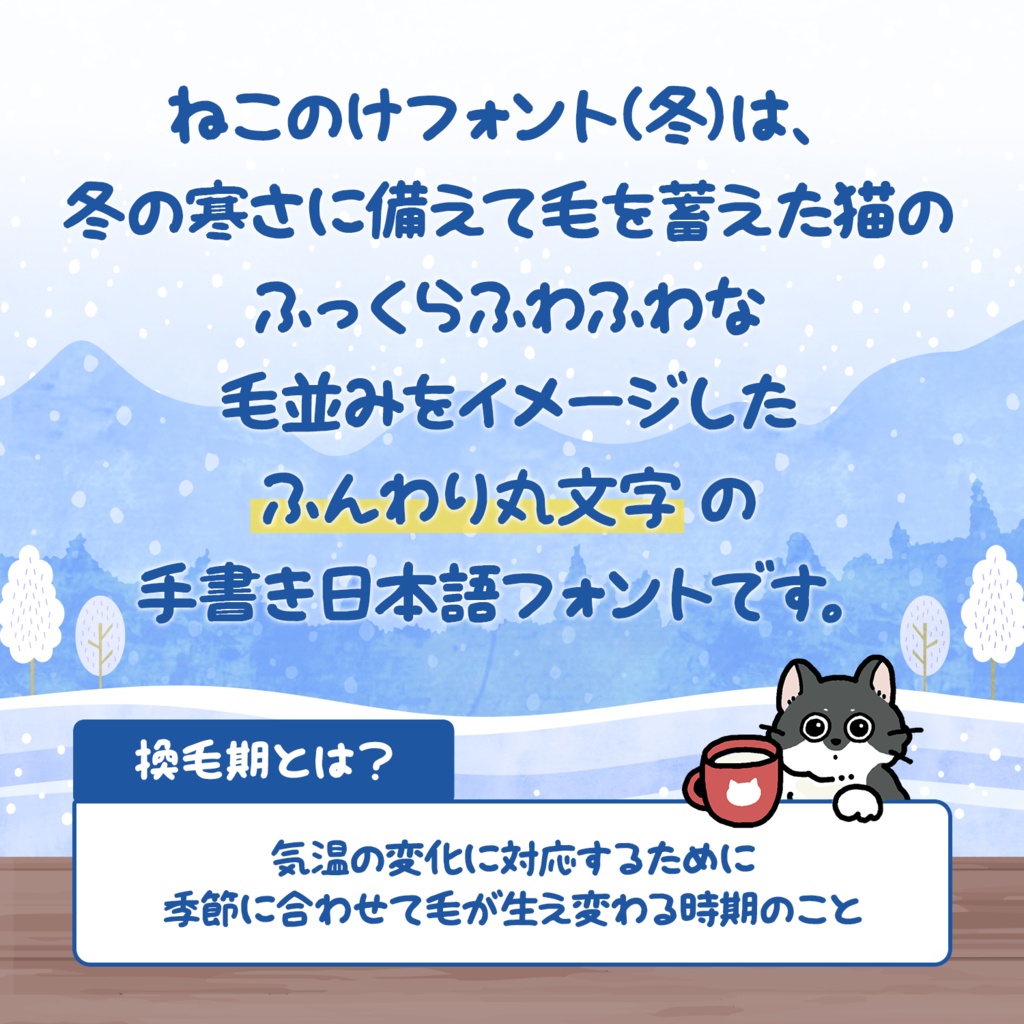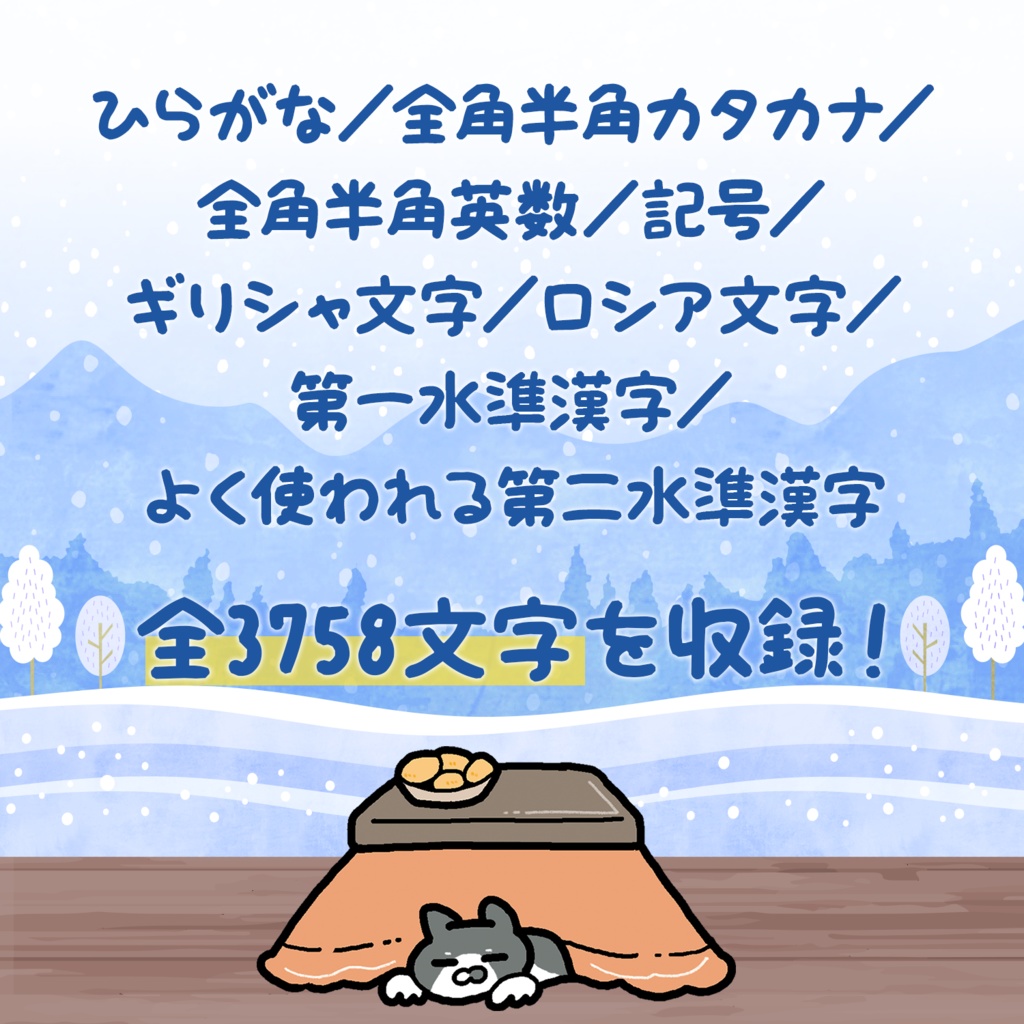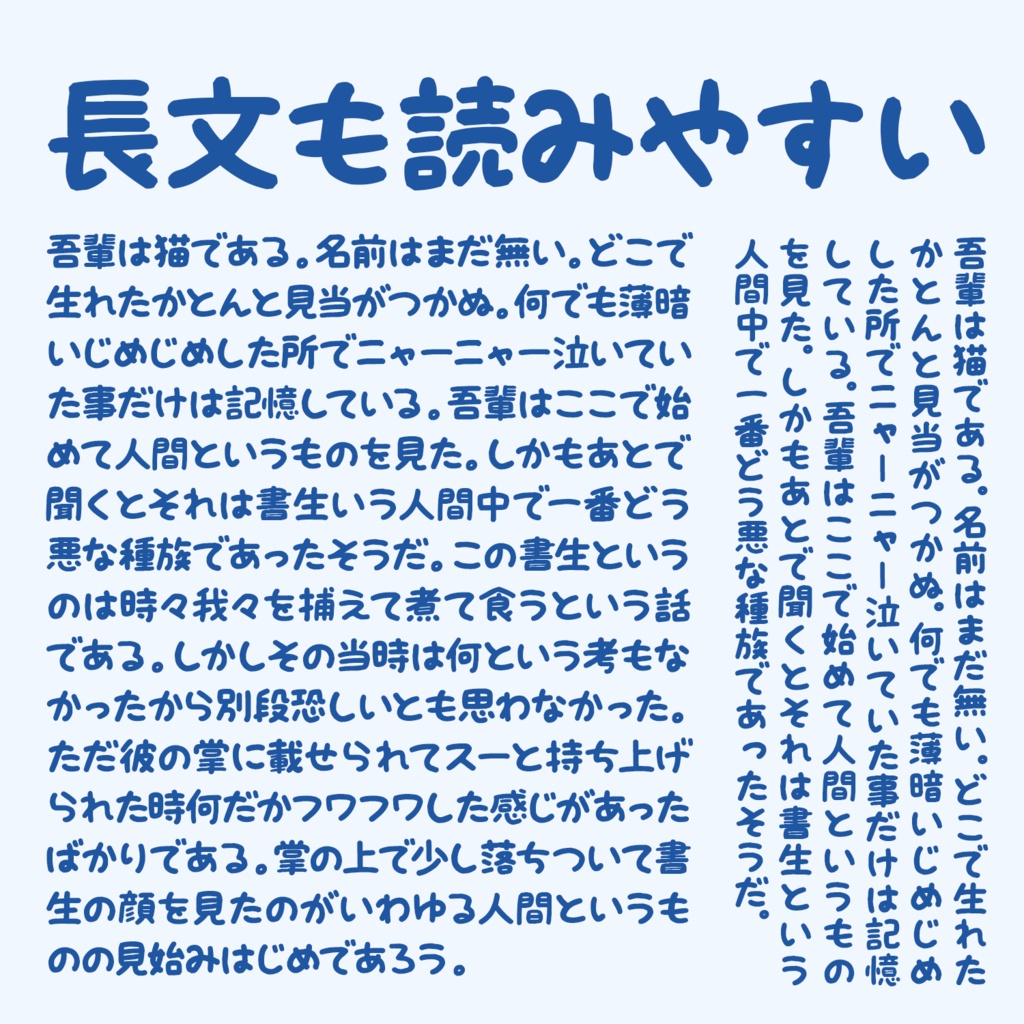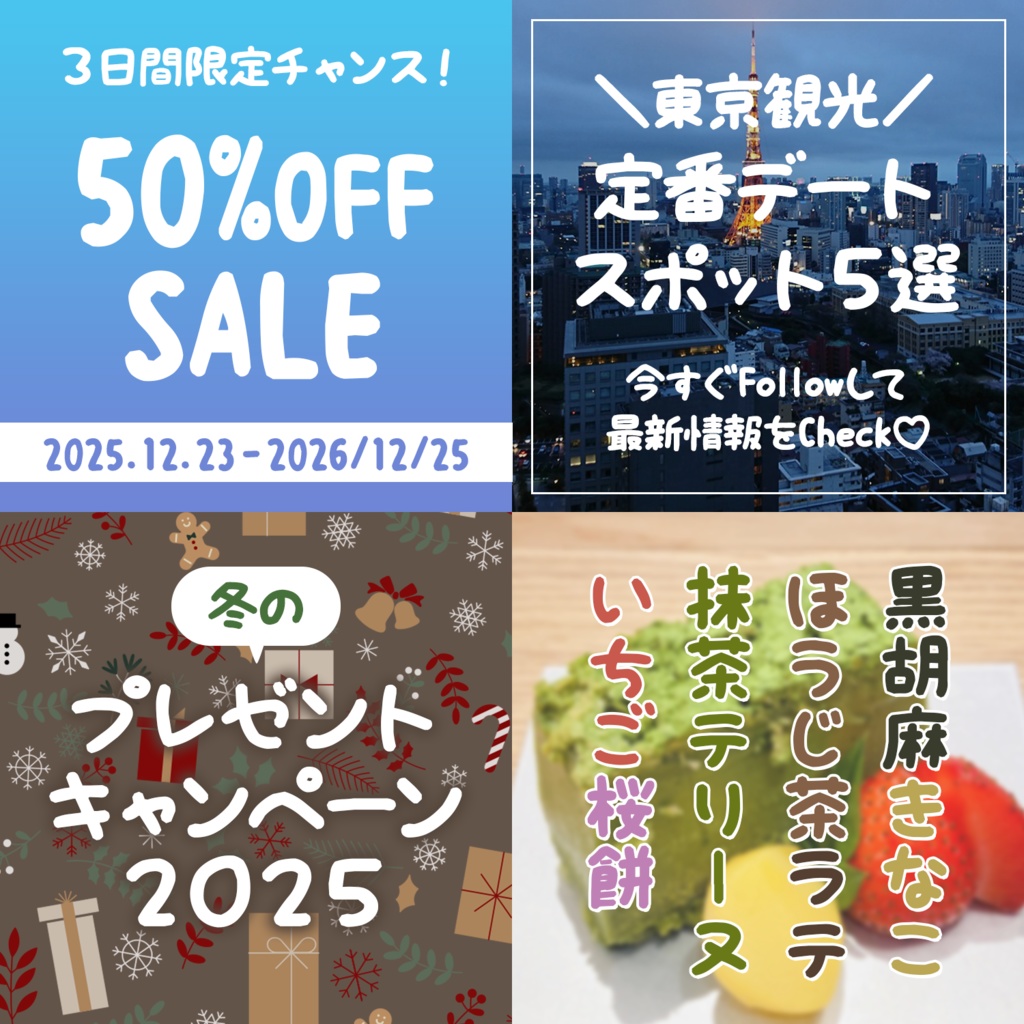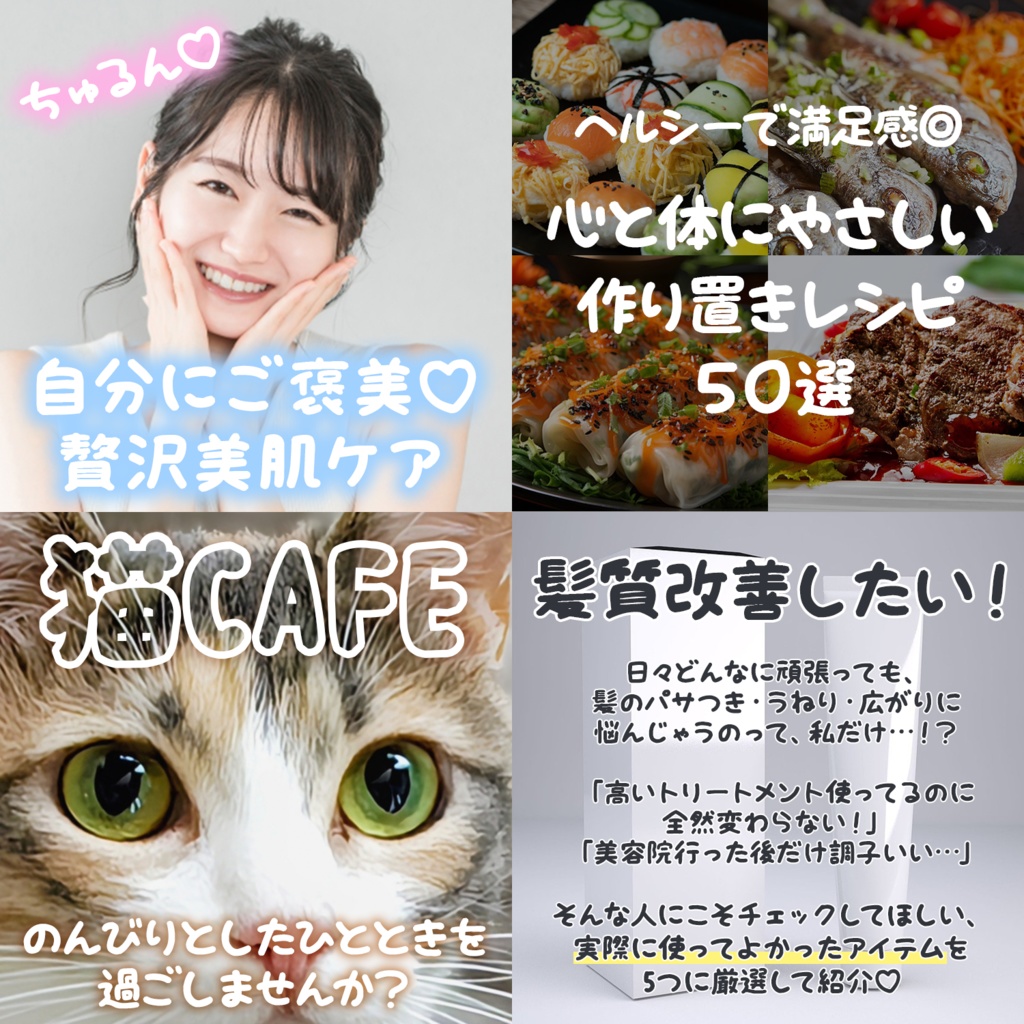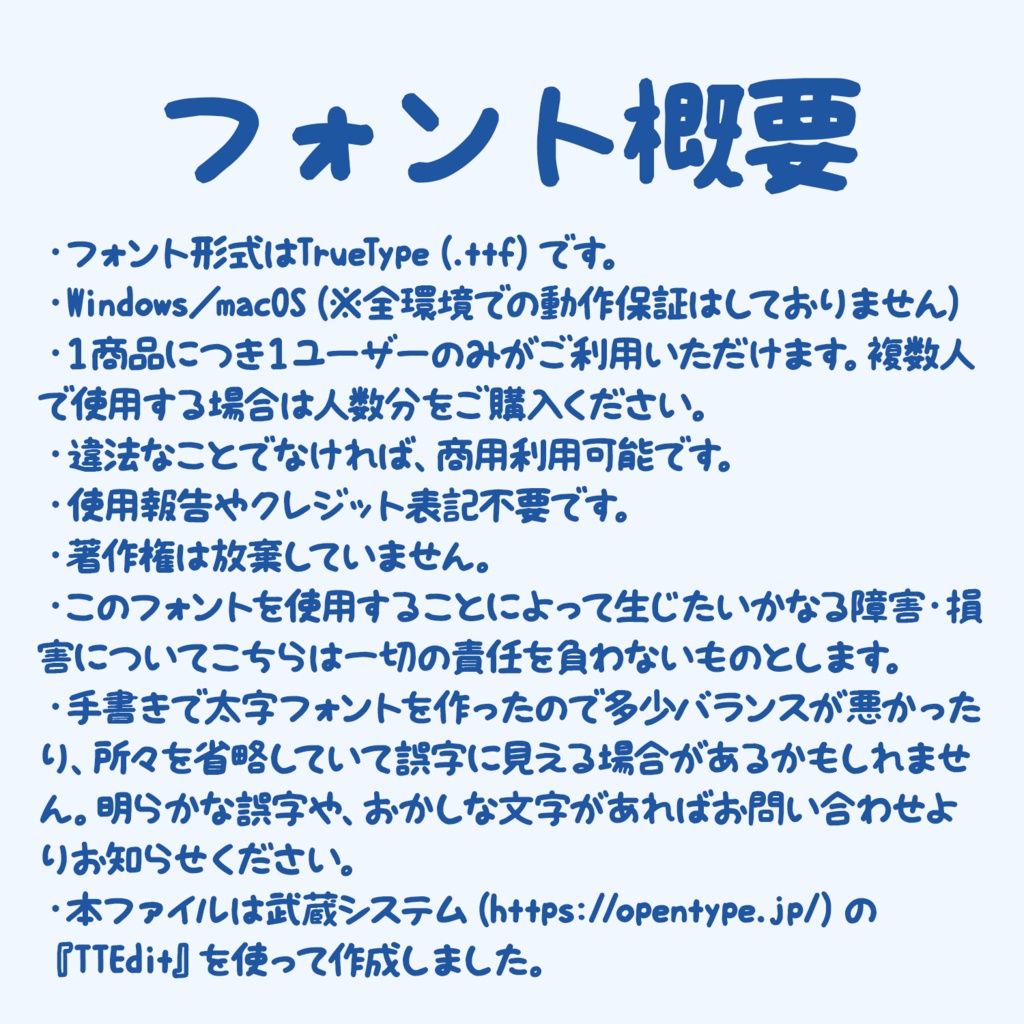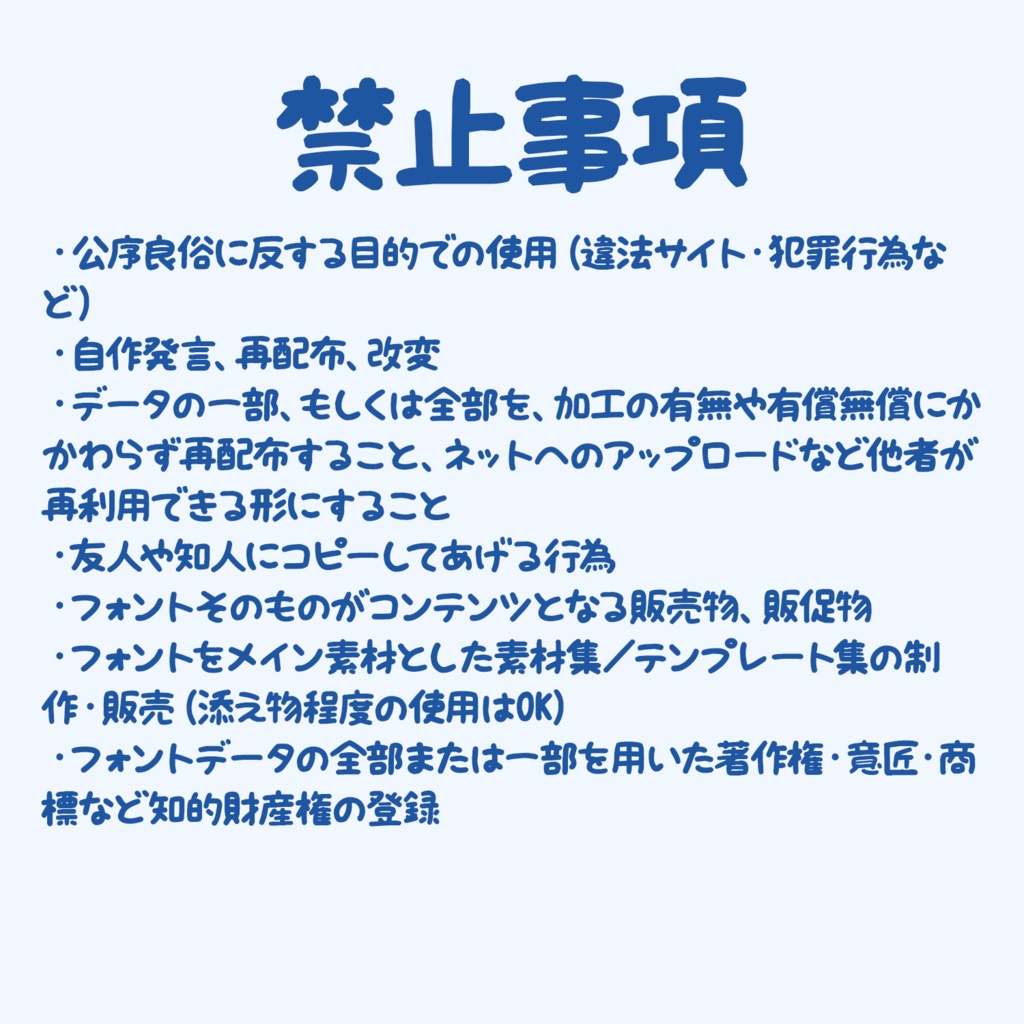
ねこのけフォント(冬)は、 冬の寒さに備えて毛を蓄えた猫の ふっくらふわふわな毛並みをイメージした ふんわり丸文字の手書き日本語フォントです。 【セット内容】 ・ねこのけフォント 冬 regular(.ttf) ・ねこのけフォント(冬)使用許諾(.txt) ・ごあいさつ(.png)
【収録文字数】
全3758文字を収録! ひらがな/全角半角カタカナ/全角半角英数/記号/ギリシャ文字/ロシア文字/第一水準漢字/よく使われる第二水準漢字 ⭐️追加文字リクエストも受け付けています! X(旧Twitter)@yurutegakiのDMよりお問い合わせください。 ※一部画数やバランスの都合により、対応できない文字もございます。 ※収録文字数が増えた場合、価格を変更する可能性があります。(既にご購入いただいた方には、追加費用なしでアップデートをご提供します)